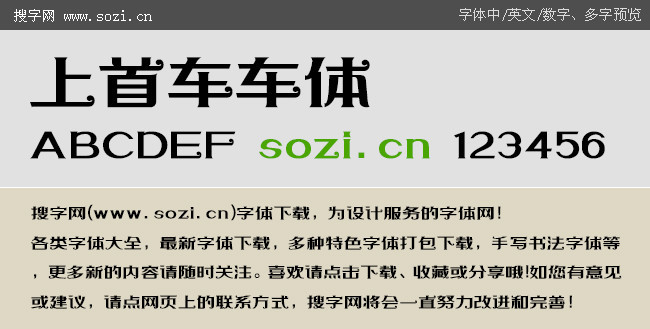
上首車車體
搜字網(wǎng)給大家提供一款上首車車體中文字體下載,上首車車體,字體風(fēng)格穩(wěn)重呈方塊形,字體筆畫(huà)豎折處細(xì)節(jié)處理,是此套字庫(kù)的亮點(diǎn)。字庫(kù)整體特征堅(jiān)硬、有力,具有現(xiàn)代、國(guó)際化的指向性,適用于搭配標(biāo)志、廣告標(biāo)語(yǔ)、商業(yè)廣告等高端屬性。